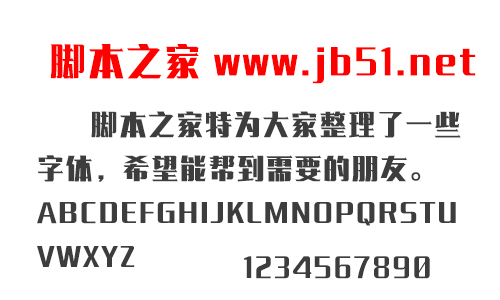
方正雪煒銳黑字體是一款時尚動感的字形,筆畫結構“橫豎”做了切角處理,讓字形外觀更加鋒利直爽、字形的左右兩側增加了尖角和力量型筆畫裝飾,筆畫“豎鉤”上提幅度較大,讓字形整體更加棱角分明,字形比例10:9,結構設計中心稍偏上,讓字形顯得高挑并具有一定的美感。字形適用于各類商業(yè)廣告、電影海報、游戲頁面海報、公司標準字、食品包裝、男性品牌、淘寶電商、網站宣傳等領域。歡迎喜歡方正雪煒銳黑字體的朋友前來下載使用。